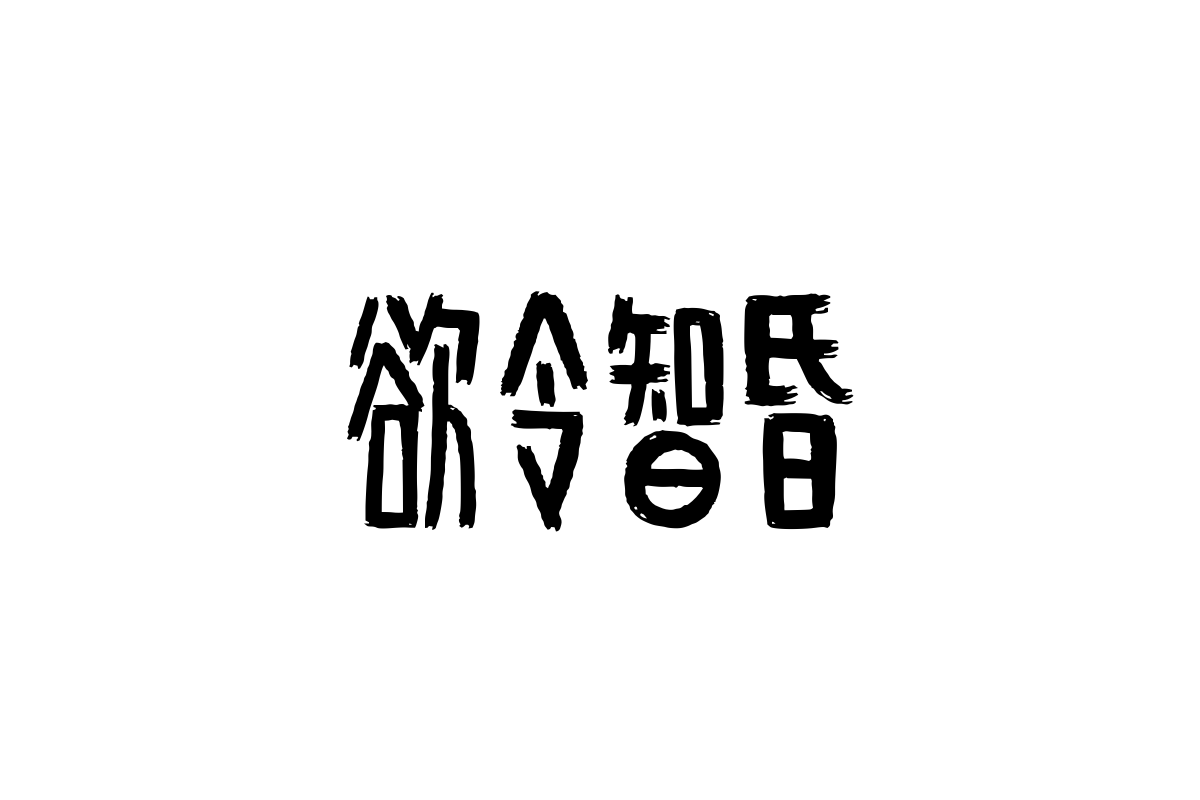
汉仪喵魂漫画体是一款专为漫画和插画设计的字体,具有独特的风格和特点。这款字体的特点是线条流畅、粗细均匀,适合用于漫画、插画等需要表现动态和细节的场景。同时,它的笔画形状独特,具有一定的艺术感,能够为作品增添独特的韵味。
汉仪喵魂漫画体的特点如下:
1. 线条流畅:该字体的线条流畅自然,能够很好地表达出漫画和插画中的动态效果。
2. 粗细均匀:字体的粗细变化适中,既不会过于夸张,也不会过于细腻,使得作品整体看起来更加和谐。
3. 笔画形状独特:该字体的笔画形状独特,具有一定的艺术感,能够为作品增添独特的韵味。
4. 适应性强:汉仪喵魂漫画体适用于各种类型的漫画和插画,无论是简单的线条描绘还是复杂的场景刻画,都能够轻松应对。
总之,汉仪喵魂漫画体是一款非常适合漫画和插画创作者使用的字体,其独特的风格和特点能够为作品增添独特的韵味和艺术感。